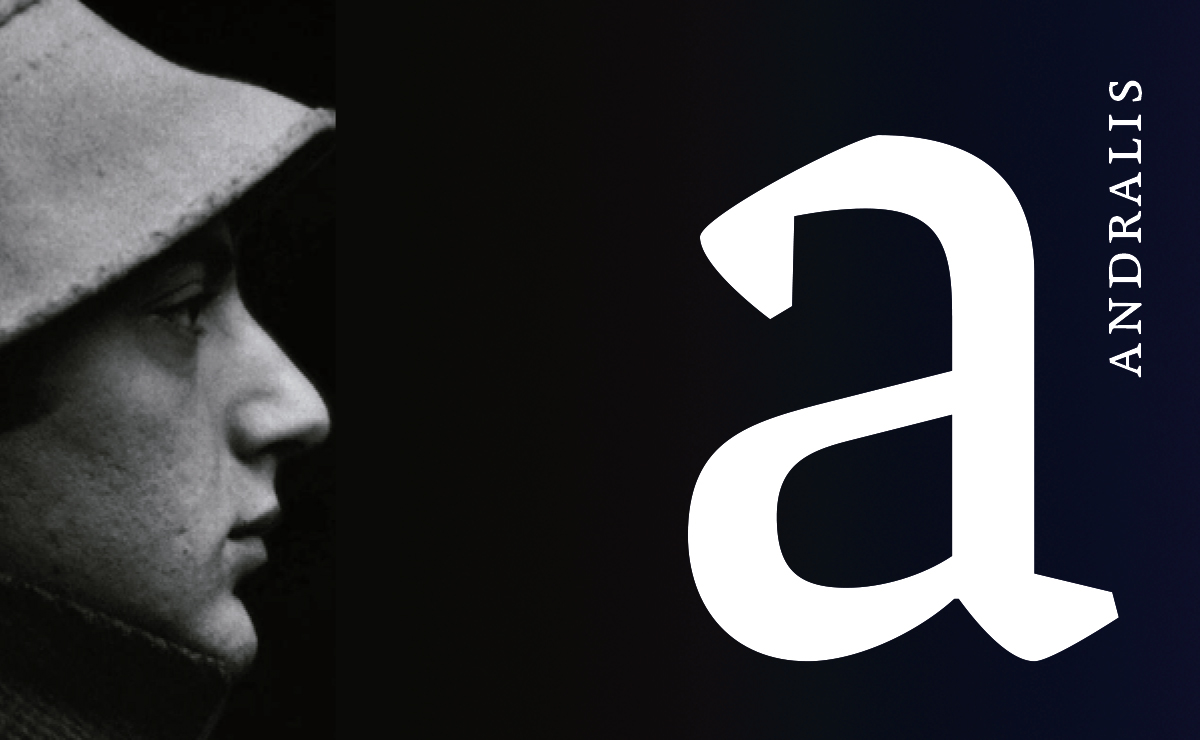
Andralis, el homenaje a un maestro
Dos grandes tipófilos
“Particularmente pienso que donde haya un buen maestro y un alumno ávido de aprender habrá una escuela, más allá de los edificios y las estructuras que los contengan.” Esta fue la respuesta de Rubén Fontana al ser preguntado sobre la necesidad de la formación universitaria para ser un buen tipógrafo.
Precisamente así es como concebía su relación con Juan Andralis, a quien veía como un maestro. Y la convicción sobre la importancia de compartir el propio conocimiento y aprender del saber de los demás, era una actitud que ambos compartían tanto como alumnos como como maestros.
También les era común el amor por la tipografía que recorre como hilo conductor la vida profesional y creadora de los dos. Desde pequeños manifestaban una atracción innata por la tipografía. En la infancia –que ambos pasaron en Buenos Aires– Juan Andralis se sentía magnetizado por la imprenta artesana y seducido por el deseo de hacer libros, mientras que Rubén Fontana se sentía fascinado por el origen y las formas de las letras. Andralis ya de niño fabricaba los libros que sus amigos habían escrito manualmente y Fontana, en su etapa entre los doce y los diecisiete años, se dejaba enseñar por el hombre encargado de la tipografía dentro del la agencia en la que entró como aprendiz.
A parte de su vocación como pintor surrealista que le llevó en 1951 a Paris, Andralis siempre estuvo de algún u otro modo muy ligado al mundo de la tipografía. En 1957, a los veintinueve años, comenzó a trabajar para el famoso diseñador Cassandre junto a Adrián Frutiger quien personalmente lo había recomendado. En ese momento Cassandre estaba trabajando en la tipografía Graphika para la empresa Olivetti.
Pasados catorce años en Paris, Andralis vuelve en 1964 a Buenos Aires por enfermedad de su padre. Allí retoma la amistad con el poeta Aldo Pellegrini con quien imprime un libro para la editorial Insurrixit y comienza una colaboración con Mario Pellegrini, el hijo de su amigo, junto a quien diseña las portadas para los libros de la editorial Argonauta. Esta nueva inmersión en el mundo de la imprenta y los libros, culmina en la apertura de su propia imprenta Archibrazo en el año 1968, que se convierte en un lugar de encuentro cultural y literario mítico de la ciudad.
Toda su experiencia y pasión por la tipografía le convirtió en un gran conocedor de la materia. En el Departamento Gráfico del Di Tella –un emblemático instituto porteño impulsor del arte, la cultura y la ciencia de los años sesenta–coincide con Rubén Fontana. Su visión hacia el mundo de las letras era muy similar. Se habían conocido ya antes y no fue casualidad que en su primer encuentro fuera un tipómetro lo que les hiciera entablar conversación.  En el mayor momento de auge del instituto di Tella, considerado el templo de las vanguardias artísticas, en el que Juan Carlos Distéfano presidió su departamento, su colaboración produjo una especialización inesperada en el campo de la tipografía. Fue la mayor etapa de aprendizaje de Fontana y fue Juan Andralis quien le enseñó o –como diría Fontana– de quién aprendió.
Una letra resistente de carácter firme
El profundo cariño y respeto de Ruben Fontana hacia Juan Andralis se evidencia con la publicación de un libro en 2001 con motivo de la gran pérdida que supuso para él y otros amigos la repentina muerte de Andralis en 1994. Este homenaje no podía reunir mejor aquello que a Andralis tanto le apasionaba: el mundo del libro y la tipografía. De hecho Fontana diseño especialmente una tipografía con la que editar el libro, e hizo de este modo un homenaje en forma de tipografía a su entrañable maestro.
La necesidad de ser una tipografía para textos prolongados combinó muy bien con otra premisa: De algún modo Fontana buscó un diseño acorde a las preferencias tipográficas de Juan Andralis. El carácter fuerte y robusto que muestra la fuente coincide con el gusto de Andralis por una mancha de texto con un gris potente. También el buen rendimiento y la buena legibilidad que exige una tipografía de lectura, fue un requisito que combinaba muy bien con esta predilección por tipografías de carácter firme y de mancha densa.
Teniendo estas premisas en mente, Fontana se topó con la escritura devanagari hindú. Esta escritura se caracteriza por el trazo horizontal del cual cuelgan los signos y que abarca el ancho de las palabras. Observó que este refuerzo horizontal facilitaba el reconocimiento y la estructura de la palabra y buscó la forma de aplicar este concepto a una letra latina tradicional. Por ello, las partes que suelen ser finas en las tipografías romanas, en la Andralis también son gruesas resultando así signos de un contorno fuerte.
Los trazos gruesos laterales y horizontales que componen cada letra crean un marco armado que ayudan al buen reconocimiento del signo. La mejora de la lectura también se produce por la aplicación de la fórmula-M de Dwiggins en la Andralis. Este principio consiste en crear una contradicción entre la contraforma interior y exterior. Se trata de engañar al ojo a través de la simplificación y hacer ver curvas donde no las hay, sobre todo a tamaños pequeños o grandes distancias.
Una tipografía para contar grandes (y pequeñas) historias
De la combinación de todas estas ideas resultó una tipografía muy bien armada de carácter fuerte y resistente. Sus formas angulares, el contraste que genera la forma interior frente a la exterior y el aspecto cuadrangular en la estructura de las letras, le dotan de un aspecto artesanal y tosco que recuerda a la letra inscripcional revocando a tiempos pasados.
En contraste a la sutileza y elegancia de las tipografías de texto clásicas, Andralis muestra un aspecto más endurecido sin perder, sin embargo, su tono amable y humano. Su rigidez y firmeza la convierten en la tipografía idónea para contar –en un contexto contemporáneo– historias de trascendencia, de mundos inventados y tiempos pasados. Andralis narra en una voz segura e imperturbable historias intensas, vivas y profundas. Nos traslada a mundos de ensueños y nos cuenta relatos apasionados, nos hace imaginar lo inexistente y nos acerca lo que el pasado dejó atrás, narra sobre lo que fue y aún sigue siendo y sobre aquello que dejó de ser y nunca se olvidará.